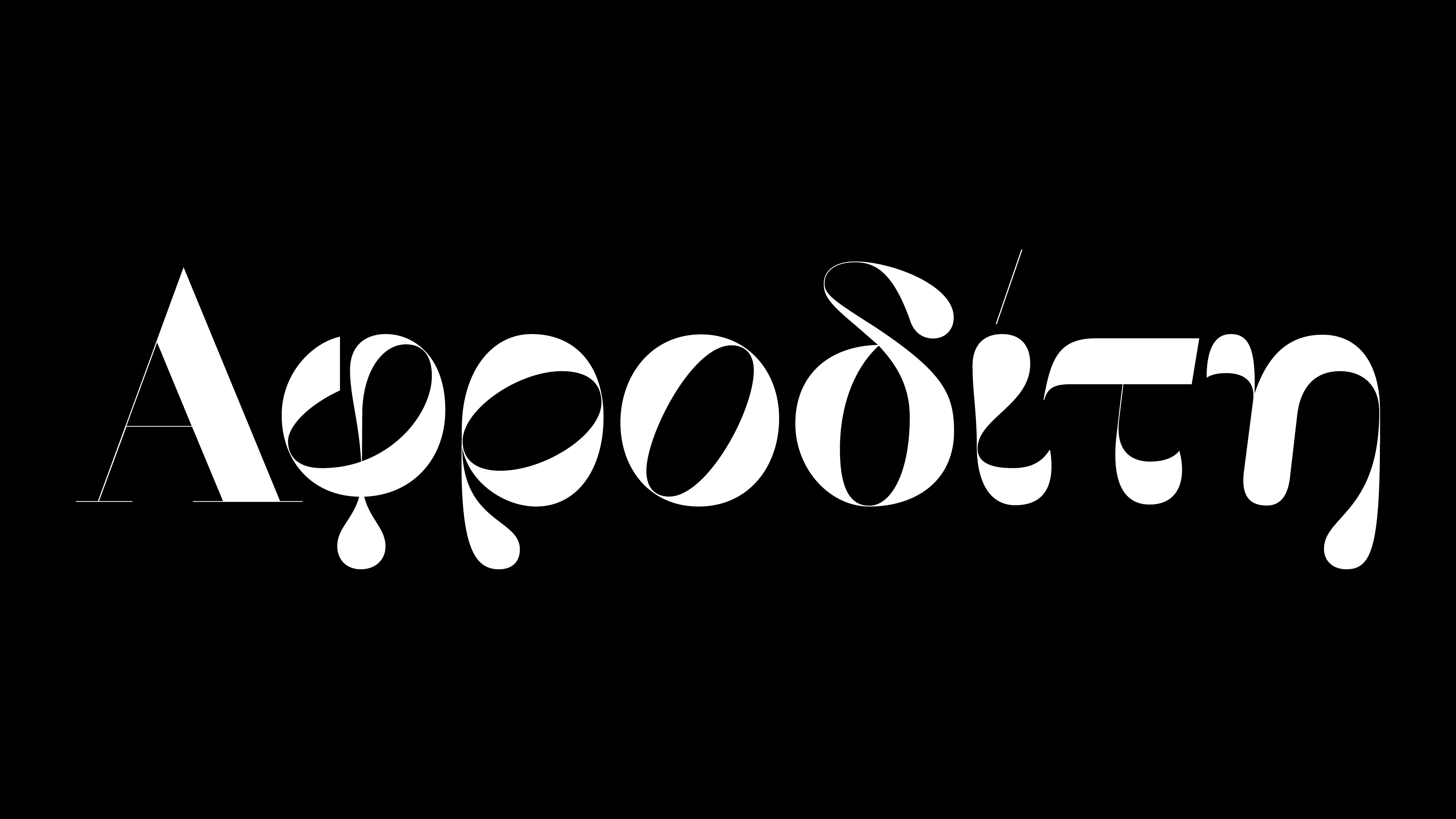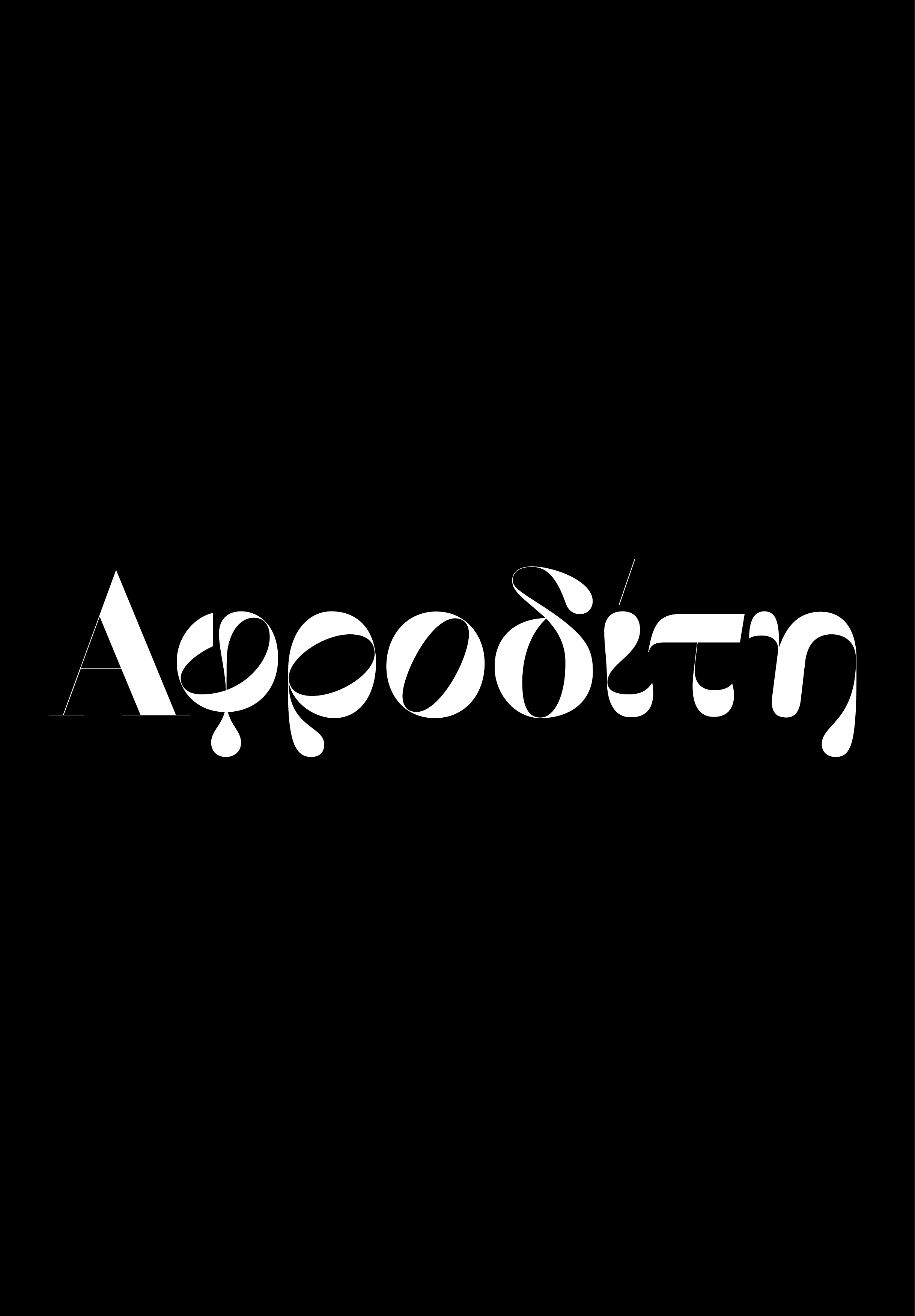
F37 Bella Greek Font Sampler
Όπως ένα μικρό μαύρο φόρεμα ή ένα προσαρμοσμένο κοστούμι, η βραβευμένη γραμματοσειρά F37 Bella είναι διαχρονικά κομψή. Συνδυάζει την περασμένη αίγλη με μια σύγχρονη αισθητική.